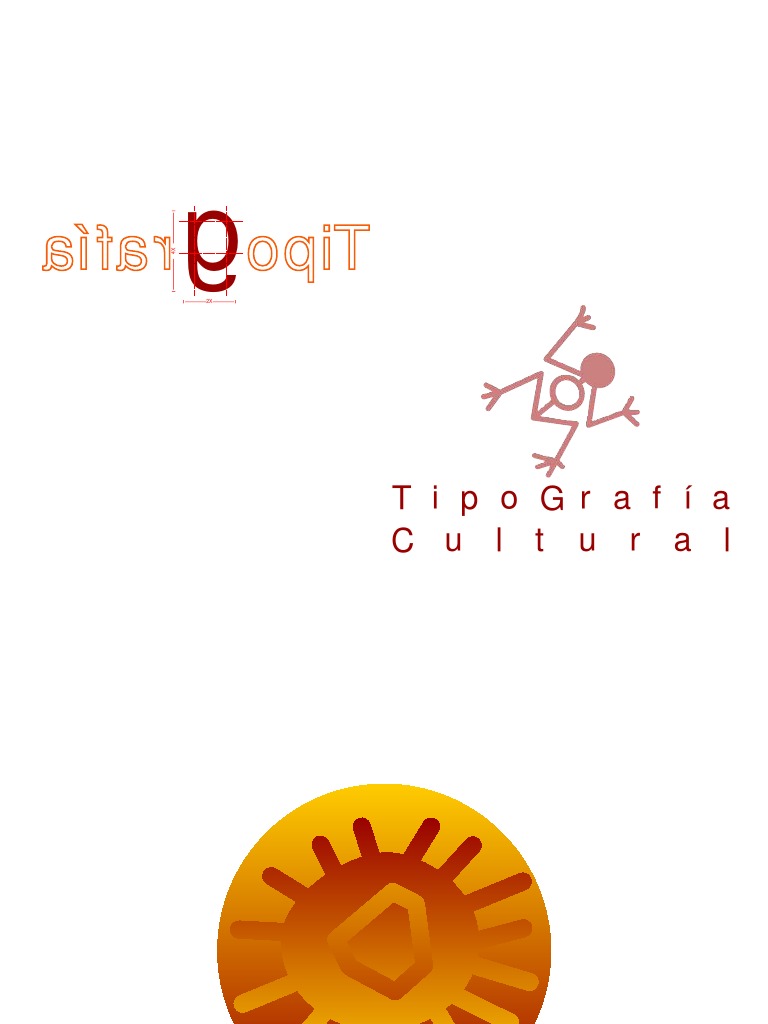
Tipografia Guane
T i p o G r a f í a
C u l t u r a l
T i p o g r a f í a C u l t u r a l
INTRODUCCIÓN
Gran parte del territorio colombiano fue habitado por
diversos grupos étnicos, culturas precolombinas que
deleitan a todo aquel que visita las zonas donde los En esta investigación, por algunas las rutas y lugares
pictogramas y petroglifos fueron plasmados, de igual que utilizaron nuestros antepasados GUANES experi-
manera sucede cuando visitamos los Museos y casas mentamos sensaciones las cuales en su mayoría
culturales donde se hallan exhibidos estos bienes fueron gratificantes, ya que pudimos conocer y tener
patrimoniales y artefactos que dan fé de una vida una idea de como funciono y ademas percibir parte
cotidiana y un desarrollo sociocultural. del estilo de vida que utilizaron nuestros indígenas.
Son pues estos objetos dignos de ser investigados Motivados e interesados en evidenciar en una cartilla
por diversas disciplinas como la Arqueología, la la riqueza cultural y con el animo de poder mostrar a
Antropología y como en este caso el Diseño Gráfico, muchas mas personas lo que esta cultura significa
que proyecta mediante esta cartilla la extinta cultura
para nuestro departamento, nos dimos a la tarea de
GUANE que pobló la región de Santander.
recopilar información mediante algunos documentos
En esta cartilla encontraremos diversos aspectos y relatos de personas ubicadas en las zonas de: La
como su economía, localización, y base económica Mesa de Los Santos, Guane, Villanueva, museos, las
entre otros. De igual manera se halla la propuesta de casas de la cultura de Bucaramanga y Floridablanca.
un diseño tipográfico cuyas bases se fundamentan en para lograr entregar un producto de una total
los pictogramas, petroglifos, en las cerámicas y satisfacción para con nosotros y con todas aquellas
textiles que los GUANES intervinieron mediante personas que de una u otra manera se encuentren
tintas naturales y grabados. Esta propuesta obedece interesadas en la preservación cultural e histórica
a un tributo, y un reconocimiento a esta cultura. indígena.